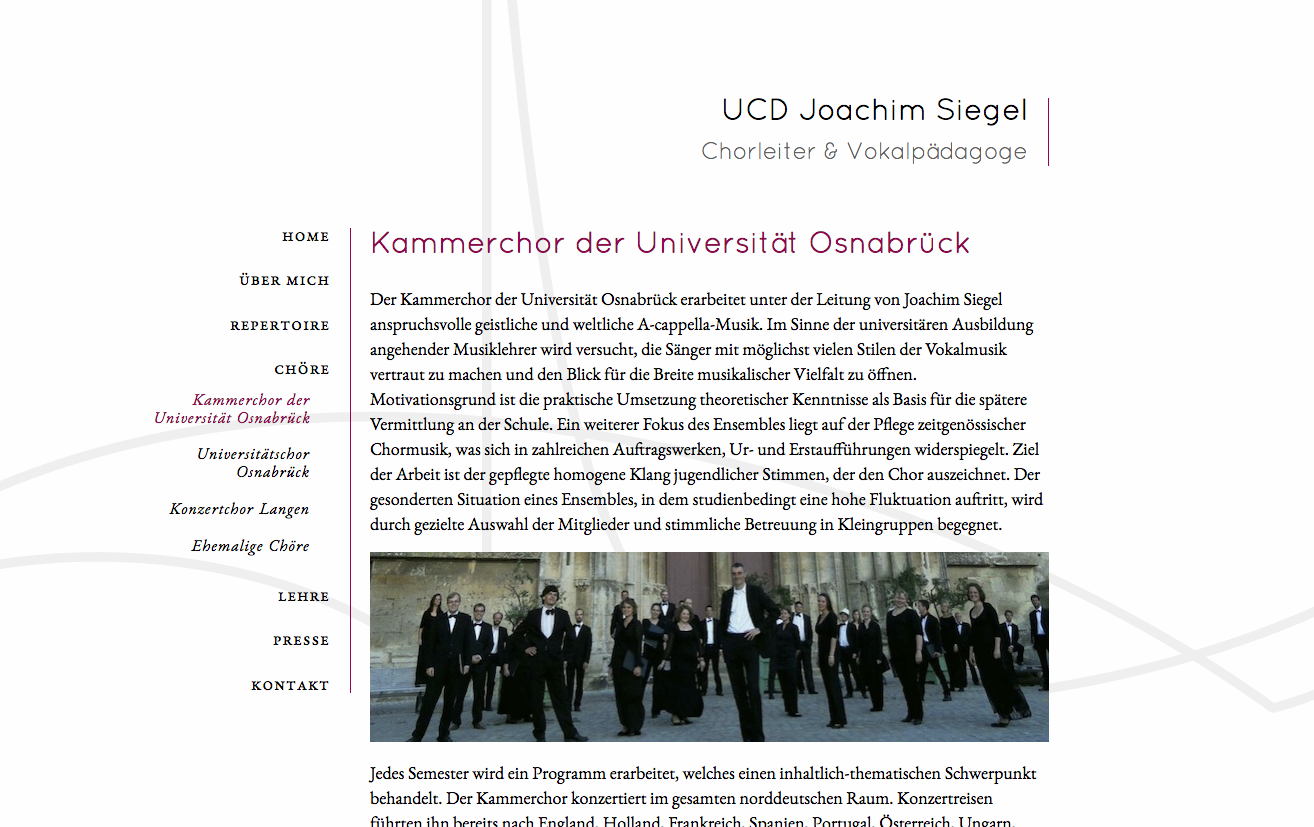
Homepage für (m)einen Chorleiter, Feedback bitte
ich gestalte und programmiere gerade eine Internetseite für meinen Chorleiter bzw. bin im Wesentlichen fertig damit und wollte nun mal um die Meinung von ein paar professionellen Augen fragen :-)
Auf den Unterseiten befindet sich bisher nur Blindtext, bspw. ist unter Lehre eine komplette Sammlung aller Überschriften von h1 bis h6 zu finden, wobei ich dem Seiteninhaber empfehlen werde nur h1 und h2 zu verwenden, und auf der Unterseite des Kammerchores, der einigen schon aus anderen Zusammenhängen bekannt ist ;-), sind die drei Bildermöglichkeiten zu sehen.
Die Fonts sind die EB Garamond und die Quicksand, beide als Webfont eingebunden. Im Hintergrund werkelt das CMS Kirby, von dem ich ganz angetan bin :biglove:
Ich hätte auch noch ein paar konkrete Fragestellungen:
• Im Prinzip wird der Inhalt im Fenster zentriert, allerdings hat die Navigation eine feste breite, so dass der linke Rand unterschiedlich groß erscheint (z.B. kleiner, wenn keine Unterebenen sichtbar sind). Würdet ihr trotzdem bei der (rechnerischen) Zentrierung bleiben, den linken Rand fix setzten oder mit Prozentwerten arbeiten und die Seite linkslastig aber nicht fixiert ausrichten?
Was meiner Meinung nach ausscheidet ist eine tatsächliche optische Zentrierung, weil dann das Menü einschließlich der Linie von Seite zu Seite hin- und herhüpft …
• Die Ausrichtung bzw. Anordnung des Fußbereichs (Impressum und Copyright) gefällt mir noch nicht wirklich, was meint ihr?
• Was sagt ihr zu den „Listen“ auf der Über- und den Repertoire-Seiten?
Zunächst stich mir das falsch angewendete kaufmännische Und ins Auge. Für mich geht das gar nicht.
Dann die immense Textmenge – bleibt die so? Ich könnte mir vorstellen, auf der ersten Ebene nur einen teaser zu bringen und eine Ebene tiefer dann die ausführlichen Texte.
ich weiß, dass das & da falsch ist, aber ich find’s ganz hübsch und an der Stelle tut mir der Regelbruch nicht weh. Mit „und“ gefällt es mir weniger, liegt aber vielleicht auch daran, dass ich mich schon an das Et gewöhnt hab …
Nein, die Textmenge ist im Moment nicht aussagekräftig. Es wird unterm Strich vermutlich weniger Text werden. Das Teaser-Konzept habe ich auf der Presse-Seite ja bereits umgesetzt auf den anderen Seiten (im wesentlich Lehre, Über) bieten sich Unterseiten thematisch eher nicht an, weswegen auch das Teaser-Konzept hier nicht sinnvoll anwendbar ist, allerdings wird sich die Textmenge auch da eher verringern. Der Lehre-Text ist grad nur so lang, um die Überschriften zu testen und der Kammerchor-Text soll die Bildformate zeigen.
Noch eine ergänzende Frage: 4. was haltet ihr von dem Begriff „Presse“ als Überschrift für die Seite, auf der Zeitungsartikel von ihm gesammelt werden? Ich bin damit noch nicht ganz glücklich, weil ich bei „Presse“ eher an ein Downloadbereich für die Presse mit Presse-Fotos und -Texten denke – mir fällt nur auch keine gescheite Alternative ein.
Die Ausrichtung bzw. Anordnung des Fußbereichs (Impressum und Copyright) gefällt mir noch nicht wirklich, was meint ihr?
Diesen Bereich würde ich nicht so hervorheben. Ev. einzeilig, Text in Grundschrift grau, linksbündig.
Im Wesentlichen finde ich die Arbeit gelungen und gut zum Thema passend.
Guten Abend und nochmal Danke für eure Rückmeldungen. :bow:
Den Fußbereich habe ich jetzt deutlich dezenter gestaltet, wie von Erwin vorgeschlagen, allerdings gefällt mir rechtsbündig besser.
Was mir nach wie vor nicht gefällt ist die Aufteilung von linken und rechtem Rand, denn der linke scheint (ist) größer wenn das Menü nicht voll aufgeklappt ist. Die Ränder sind nur gleich, wenn man sich im Bereich „Chöre“ befindet. Hättet ihr da noch eine Idee?
Meiner Ansicht nach verliert die ganze Seite an Spannung, wenn die Ränder gleich sind. Die Links würden auch sonst eingeengt wirken.
Danke, du würdest es also so lassen, wie’s ist?!